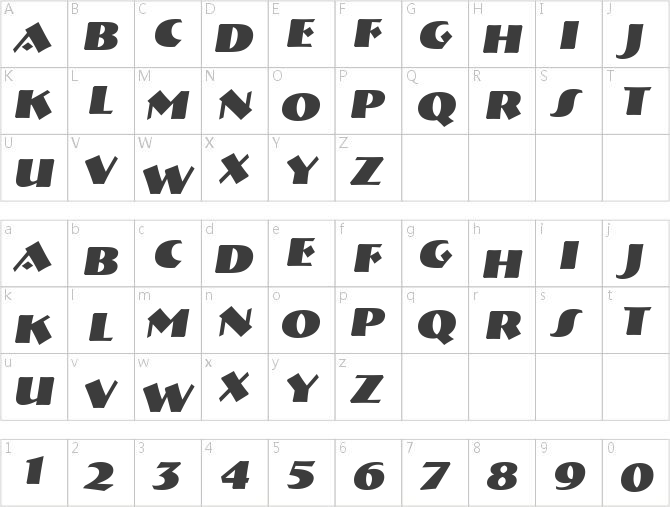
a_Bremen-BoldItalic
a_Bremen-BoldItalic介紹
a_Bremen-BoldItalic字體字庫是一款讓人賞心悅目、百看不厭的英文字體,適合各類廣告和產(chǎn)品包裝設(shè)計應(yīng)用,字體大小0.05MB,格式為ttf字體,上傳用戶是快樂圍棋,作者/版權(quán)方為未知